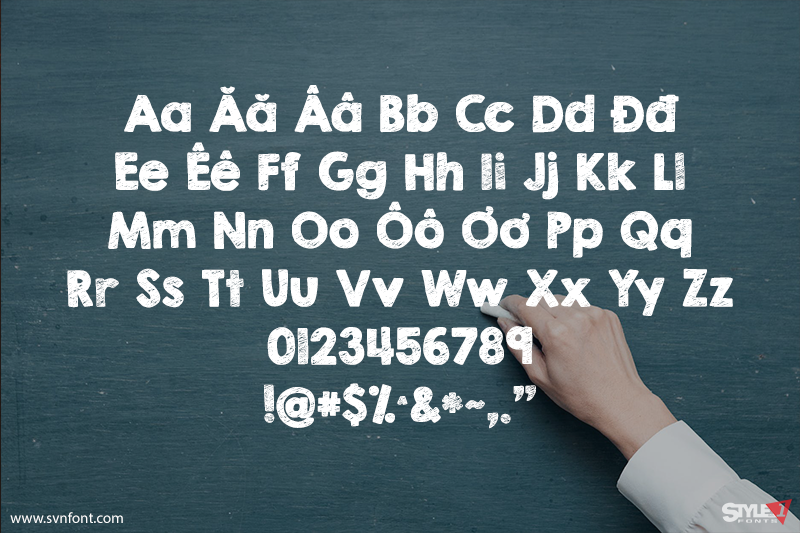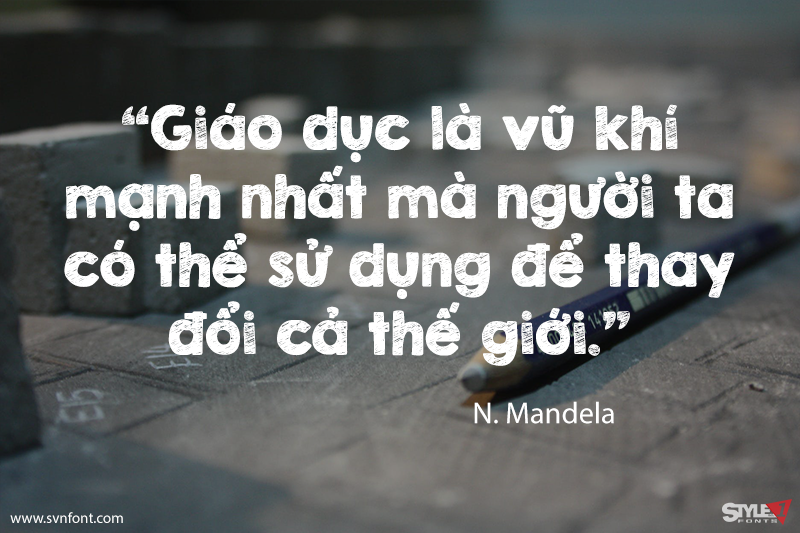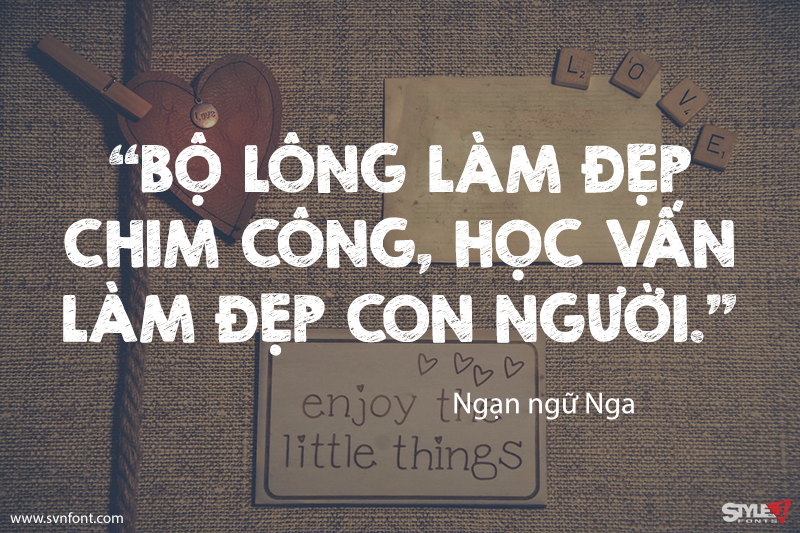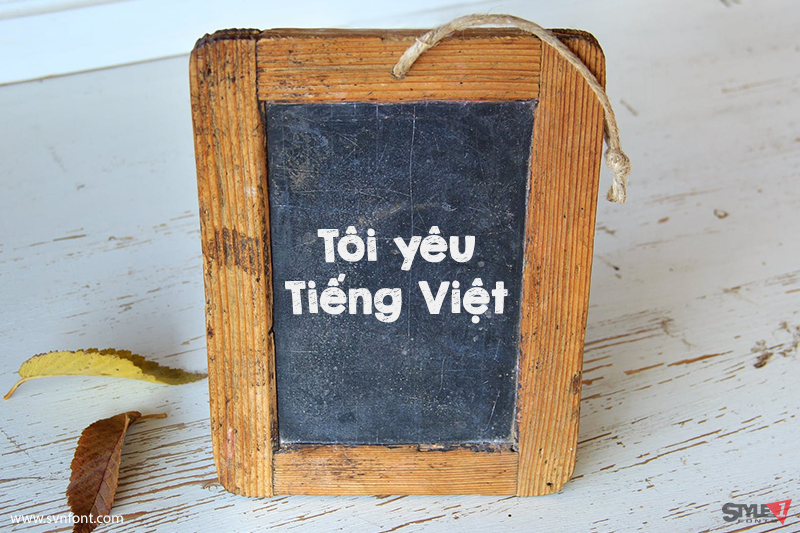
KG Broken Vessels Sketch, một font mô phỏng kiểu chữ vẽ tay từ phấn, sáp hay bút… với hiệu ứng tô chữ phác họa, font thích hợp cho thiết kế về học đường, trẻ em, đồ chơi,…
Nhà thiết kế: Kimberly Geswein